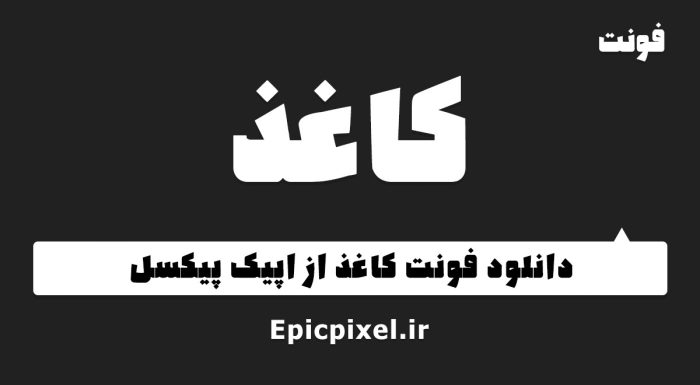
فونت کاغذ فارسی
جذابیت تایپوگرافی دانلود فونت کاغذ برای ارتقاء پروژههای طراحی شما
فونتهای فارسی نقش بسزایی در انتقال پیام و برقراری ارتباط بصری مؤثر دارند. در دنیای طراحی گرافیک، انتخاب فونت مناسب میتواند به طرز چشمگیری بر زیبایی و تأثیرگذاری پروژههای شما بیفزاید. اگر به دنبال یک فونت خاص و برجسته برای جلب توجه مخاطب هستید، دانلود فونت کاغذ را به شما پیشنهاد میکنیم.
فونت کاغذ چیست؟
فونت کاغذ، با نام اصلی «کاغذ الف»، یک فونت فارسی با وزن سنگین (Bold) است که برای عناوین، سرصفحهها و پروژههای تبلیغاتی مانند بیلبورد، پوستر و بنرهای بزرگ ایدهآل است. این فونت در سال ۱۳۹۹ طراحی و منتشر شده است.
ویژگیهای کلیدی فونت کاغذ
- قلم سنگین و برجسته: ویژگی اصلی فونت کاغذ، وزن و ضخامت بالای آن است که باعث میشود حروف خوانایی عالی در ابعاد بزرگ داشته باشند.
- ایجاد حس قدرت و استحکام: وزن بالای فونت، حس قدرت، استحکام و جدیت را به طرحهای شما القا میکند. این ویژگی برای پروژههایی با ماهیت تبلیغاتی یا اطلاعرسانی رسمی بسیار مناسب است.
- خوانایی مناسب در ابعاد بزرگ: برخلاف برخی فونتهای تزئینی با وزن بالا، فونت کاغذ خوانایی خود را در ابعاد بزرگ حفظ کرده و باعث خستگی چشم مخاطب نمیشود.
- ایجاد تمایز و جلب توجه: وزن و ضخامت بالای فونت کاغذ باعث میشود حروف به خوبی از پسزمینه متمایز شوند و توجه مخاطب را به خود جلب کنند.
- قابل استفاده برای طیف وسیعی از پروژهها: با وجود ماهیت تبلیغاتی برجسته، فونت کاغذ قابلیت استفاده در طیف وسیعی از پروژهها مانند طراحی لوگو، جلد کتاب و بستهبندی را نیز داراست.
همانطور که اشاره شد، فونت کاغذ به دلیل وزن و ضخامت بالا، بیشتر برای پروژههای با ابعاد بزرگ و نیازمند جلب توجه مخاطب مناسب است. در ادامه به برخی از کاربردهای کلیدی این فونت اشاره میکنیم:
- عناوین و سرصفحهها: فونت کاغذ برای طراحی عناوین و سرصفحههایی که میخواهید در نگاه اول خودنمایی کنند، بسیار کاربردی است.
- پوستر و بنرهای تبلیغاتی: وزن بالای فونت به آن قدرت و تأثیرگذاری زیادی در جلب توجه مخاطب در فضاهای شلوغ شهری میبخشد.
- طراحی لوگو: اگر به دنبال لوگویی با ظاهری قدرتمند و ماندگار هستید، فونت کاغذ میتواند گزینهای مناسب برای بخش نوشتاری لوگو باشد.
- جلد کتاب و بستهبندی: استفاده از فونت کاغذ برای طراحی جلد کتاب یا بستهبندی میتواند محصول شما را از سایر رقبا متمایز کند.
- عناوین وبسایت و اپلیکیشن: برای ایجاد ظاهری خاص و برجسته در عناوین وبسایت یا اپلیکیشن خود، فونت کاغذ قابل استفاده است.
مزایای دانلود فونت کاغذ
با دانلود فونت کاغذ و استفاده از آن در پروژههای طراحی خود، از مزایای زیر بهرهمند خواهید شد:
- ارتقاء سطح حرفهای پروژهها: فونت کاغذ با ظاهر خاص و برجسته خود میتواند سطح حرفهای و جذابیت بصری پروژههای شما را به طور قابل توجهی ارتقاء دهد.
- جلب توجه مخاطب: وزن و ضخامت بالای فونت به آن قدرت زیادی در جلب توجه مخاطب در نگاه اول میبخشد. این ویژگی برای بازاریابی و تبلیغات بسیار سودمند است.
- ایجاد تمایز و به یاد ماندنی بودن: ظاهر منحصربهفرد فونت کاغذ باعث میشود پروژههای شما از سایرین متمایز شده و در ذهن مخاطب ماندگار شود.
- قابل استفاده در کنار سایر فونتها: با توجه به ماهیت خاص فونت کاغذ، میتوان آن را با فونتهای سبکتر برای بخشهای متن پروژه ترکیب کرد.
با وجود مزایای فراوان، استفاده از فونت کاغذ نیازمند رعایت نکاتی است تا به بهترین نحو در پروژههای شما جای بگیرد. در ادامه به برخی از این نکات اشاره میکنیم:
- استفاده بهینه: به دلیل وزن و ضخامت بالای فونت، استفاده بیش از حد از آن در یک پروژه میتواند باعث خستگی چشم مخاطب و آشفتگی بصری شود. بهتر است از فونت کاغذ برای عناوین و بخشهای مهم استفاده کنید و برای متن اصلی از فونتهای سبکتر و خواناتر بهره ببرید.
- ترکیب با فونتهای دیگر: برای ایجاد تعادل و خوانایی بیشتر، فونت کاغذ را با فونتهای سبکتر و ظریفتر ترکیب کنید. به عنوان مثال، میتوانید از فونت کاغذ برای عنوان و از فونتهای سبکتر برای متن توضیحات استفاده کنید.
- توجه به فضای خالی: به دلیل ضخامت بالای حروف، فونت کاغذ به فضای خالی بیشتری در اطراف خود نیاز دارد. از قرار دادن حروف در کنار یکدیگر یا حاشیههای باریک خودداری کنید.
- انتخاب رنگ مناسب: برای حفظ وضوح و خوانایی حروف، از رنگهای متضاد با پسزمینه استفاده کنید. به عنوان مثال، اگر از فونت کاغذ مشکی استفاده میکنید، آن را روی پسزمینهای با رنگ روشن قرار دهید.
- آزمایش و بررسی: قبل از استفاده نهایی از فونت کاغذ در پروژههای خود، حتماً آن را در اندازههای مختلف و با رنگهای مختلف امتحان کنید تا بهترین نتیجه را به دست آورید.
1. فونت کاغذ چه نوع فونتی است؟
دانلودفونت کاغذ یک فونت فارسی با وزن سنگین (Bold) است که برای عناوین، سرصفحهها و پروژههای تبلیغاتی مانند بیلبورد، پوستر و بنرهای بزرگ ایدهآل است.